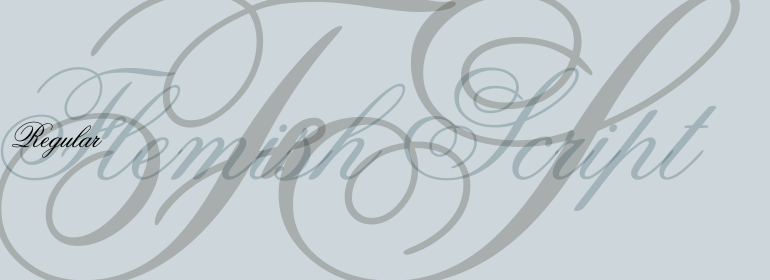
Flemish Script™
Flemish Script™,这款字体结构工整、笔画清晰,兼顾美观与易读性,适用于标题、正文、海报、包装、LOGO 等多种场景。字形优雅稳定,风格百搭耐看,适配日常排版与创意设计,让文字呈现更舒适、更具质感。Flemish Script™一笔一画,皆是细节,以均衡的比例、流畅的线条打造舒适视觉体验,字形端正大气,风格简约现代。无论是商业设计、品牌宣传还是日常排版,都能轻松驾驭,让文字更有格调与力量。Flemish Script™字体下载。
字体品牌: Bitstream(Monotype) 设计师:暂无 字体分类: 字体属性:外文 字符集:Unicode 发布时间: 2018